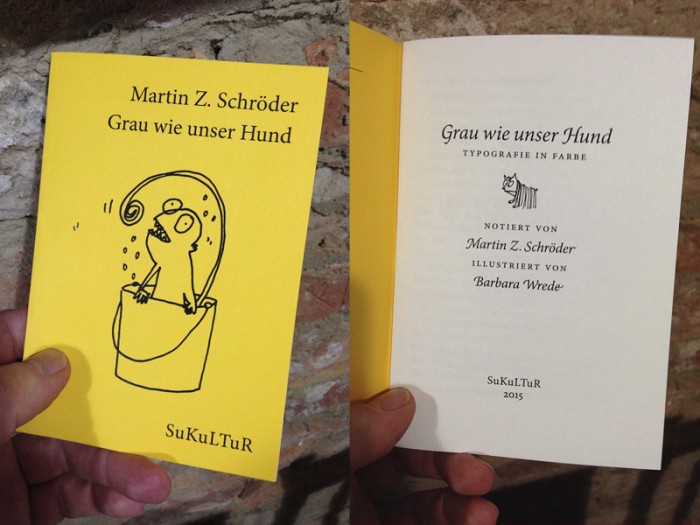
Zehn ausgedachte Dialoge über Druckfarben
Zehn Dialoge über Druckfarben: welche Angaben Drucker und Designer von ihren Kunden erhalten, wie sich Schrift mit der Farbe ändern kann, wie ein Drucker über Farbe spricht, wie ein Designer über eine Nichtfarbe spricht, alles in unterhaltsamer Gesprächsform geschrieben, typografisch etwas aufgebrezelt und mit Zeichnungen versehen. Im handlichen Jackentaschenformat DIN A6.
Martin Z. Schröder
Grau wie unser Hund
Typografie in Farbe
Illustriert von Barbara Wrede
Leseprobe:
Really Orange
»Was würden Sie sagen, wenn ich mir ein bestimmtes Orange für unsere Wortmarke wünsche?«
»Was sollte ich denn dazu zu sagen haben können?«
»Na ja, das Orange lieber etwas rötlicher? Oder irgendwie verschwommen, so leicht pastellig oder so?«
»Orange ist eine eindeutige Angelegenheit. Als Druckfarbe ist Orange unempfindlich. Etwas mehr Rot, etwas mehr Gelb, das ist egal. Also in der Mode mag es wichtige Nuancen geben, aber bei Drucksachen würde ich gar nicht darüber nachdenken. Dunkler, heller, egal. Es wird immer als Orange wahrgenommen. Es gibt hierzulande keine empfindlichen Assoziationen. Die Farbe kommt bei uns in der Natur kaum vor, wir haben kein Gefühl für ihre Nuancen. Es gibt vielleicht in Asien und Afrika ein paar orangefarbene Vögel, Fische und Blumen und vielleicht auch Berge, und wer dort wohnt, versteht etwas von Orange. Viel mehr als wir. Orange ist in der nördlichen Welt kaum zu sehen. Abgesehen von der Berliner Stadtreinigung.«
»Aber die Sonne?«
»Die ist weiß. Na ja, abends, okay, da macht sie manchmal ein paar Minuten oranges Licht. Aber da bildet Orange nur einen Übergang von Gelb zu Dunkelrot. Und als Fläche. Wir aber sprechen von Schrift, also Linien. Sie sagen, ich soll Orange drucken, ich drucke Orange, that’s it.«
»Und Sie würden Kapuzinerkresse, Lampion- und Ringelblumen, Begonien und Goldlack, Lilien, Nelken, Habichtskraut sowie Clementinen, Mandarinen und Satsuma allesamt nur in Ihrem einen Orange drucken? Really?«
»Ich muß jetzt leider, leider zum Zahnarzt.«